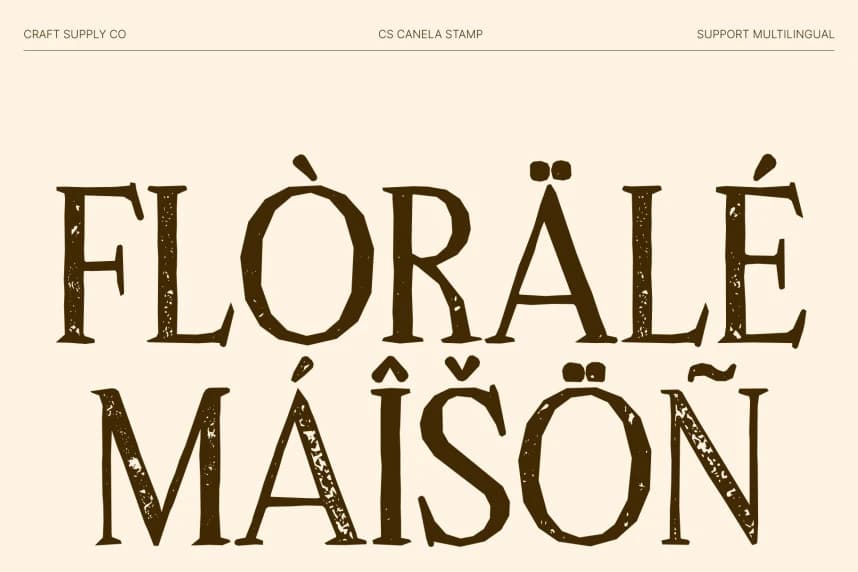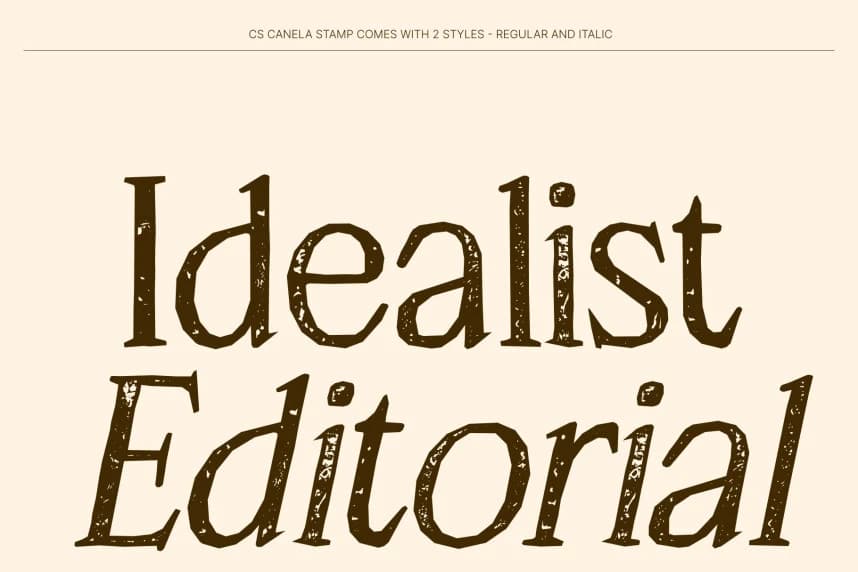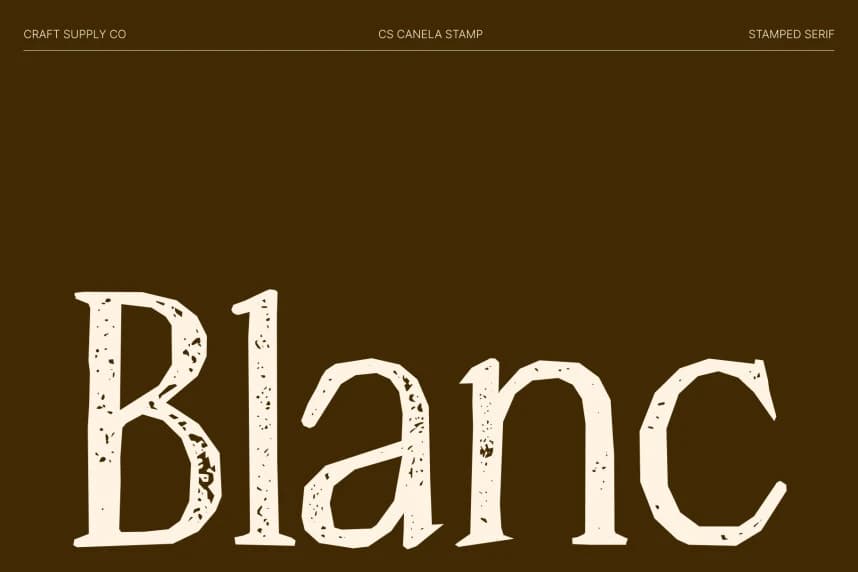
CS Canela Stamp font
CS Canela Stamp Font – Zamansız Şıklık ve Vintage Doku ile Şık Serif Yazı Tipi. Temiz, İnce Hatlara Sahip ve Sanatsal Karaktere Sahip Zarif Bir Serif Yazı Tipidir. Bu, temiz, ince harf biçimleriyle tasarlanmış zarif bir serif yazı tipidir ve zarafeti ile güven duygusu verir.
CS Canela Stamp Font – Vintage Doku ile Zamansız Zarafet. Temiz, ince hatlara ve sanatsal karaktere sahip zarif bir serif. Bu, zarafeti ve güveni yansıtan temiz, ince harf biçimlerine sahip tasarlanmış bir zarif serif yazı tipidir.